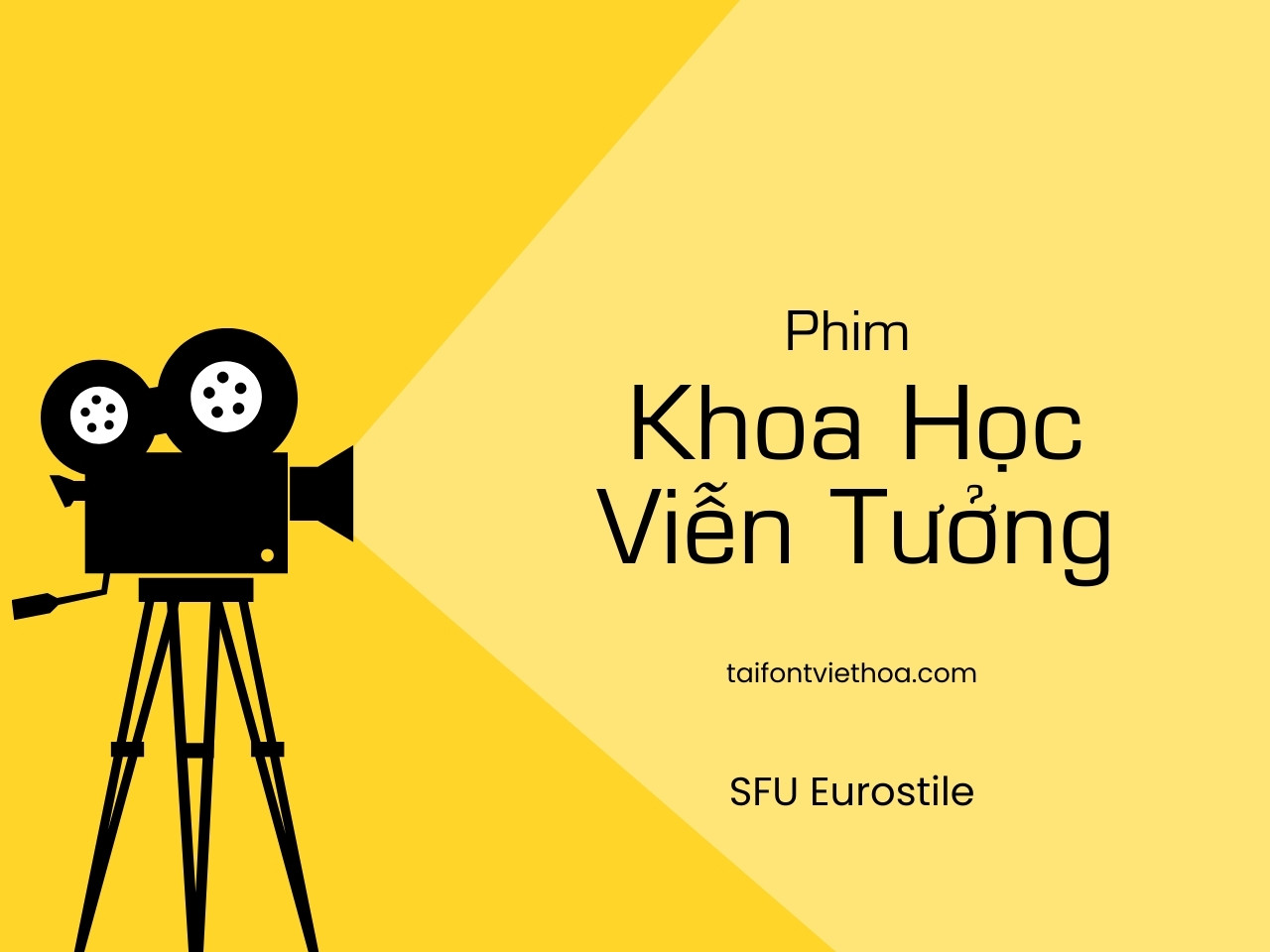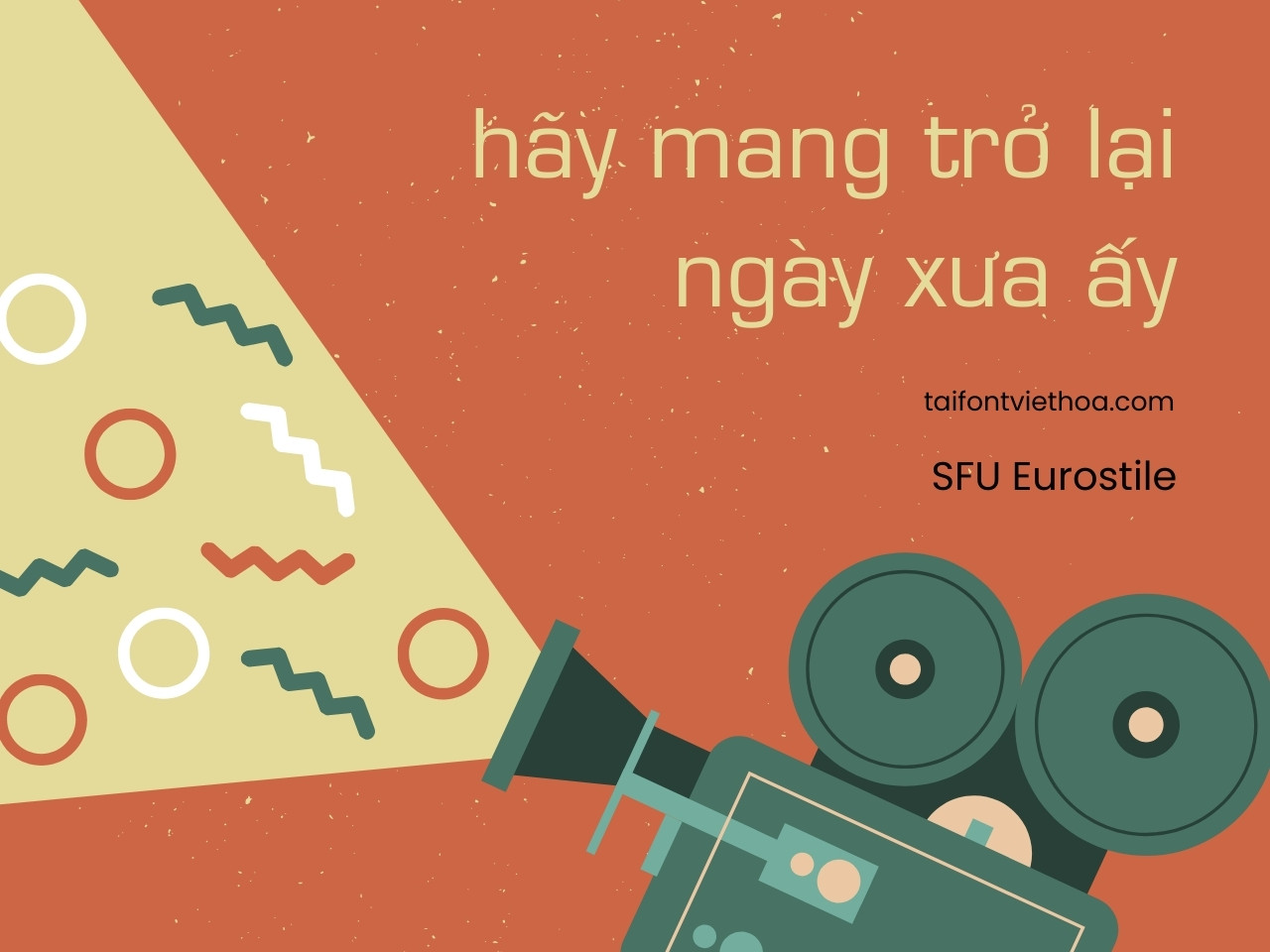
Font việt hóa SFU Eurostile
Giới thiệu về font SFU Eurostile – Kiểu chữ biểu tượng của công nghệ và tương lai
SFU Eurostile là phiên bản Việt hóa của font Eurostile – một kiểu chữ sans-serif hình học nổi tiếng, được thiết kế bởi Aldo Novarese vào năm 1962 tại hãng Nebiolo (Ý). Eurostile nhanh chóng trở thành biểu tượng của thiết kế công nghệ và hiện đại, nhờ các đặc trưng góc bo tròn, chiều ngang rộng và cảm giác mang đậm tính kỹ thuật. Font này từng xuất hiện trên bảng điều khiển, thiết bị điện tử, logo hãng xe, giao diện phim khoa học viễn tưởng và các hệ thống công nghiệp.
Phiên bản SFU Eurostile đã được Việt hóa đầy đủ, hỗ trợ dấu tiếng Việt và hơn 100 ngôn ngữ khác. Tải Font Việt hóa đã chọn lọc và giới thiệu font này nhằm cung cấp giải pháp thiết kế tối ưu cho những ai làm việc trong lĩnh vực công nghệ, kỹ thuật số hoặc thiết kế giao diện mang phong cách tương lai.
Đặc trưng công nghệ, mạnh mẽ và ứng dụng đa dạng của SFU Eurostile
SFU Eurostile sở hữu thiết kế sans-serif hiện đại, các ký tự có hình dạng vuông vức nhưng được bo góc nhẹ, tạo cảm giác công nghiệp mà không khô cứng. Font có các biến thể đậm – mảnh, nghiêng – thẳng, dễ dàng kết hợp để phân cấp nội dung và thiết lập hệ thống trực quan mạnh mẽ. Đặc biệt, dáng chữ ngang và chắc chắn giúp font nổi bật trong các tiêu đề, logo hoặc giao diện kỹ thuật số.
Ứng dụng lý tưởng: thiết kế app, website, dashboard, hệ thống hiển thị số, thương hiệu công nghệ, bảng mạch điện tử, poster phim khoa học viễn tưởng và nhận diện sản phẩm công nghiệp. Ngành nghề phù hợp: công nghệ, kỹ thuật số, điện tử, phần mềm, startup, xe hơi, viễn thông và các lĩnh vực hướng đến sự hiện đại, chính xác và chuyên nghiệp.